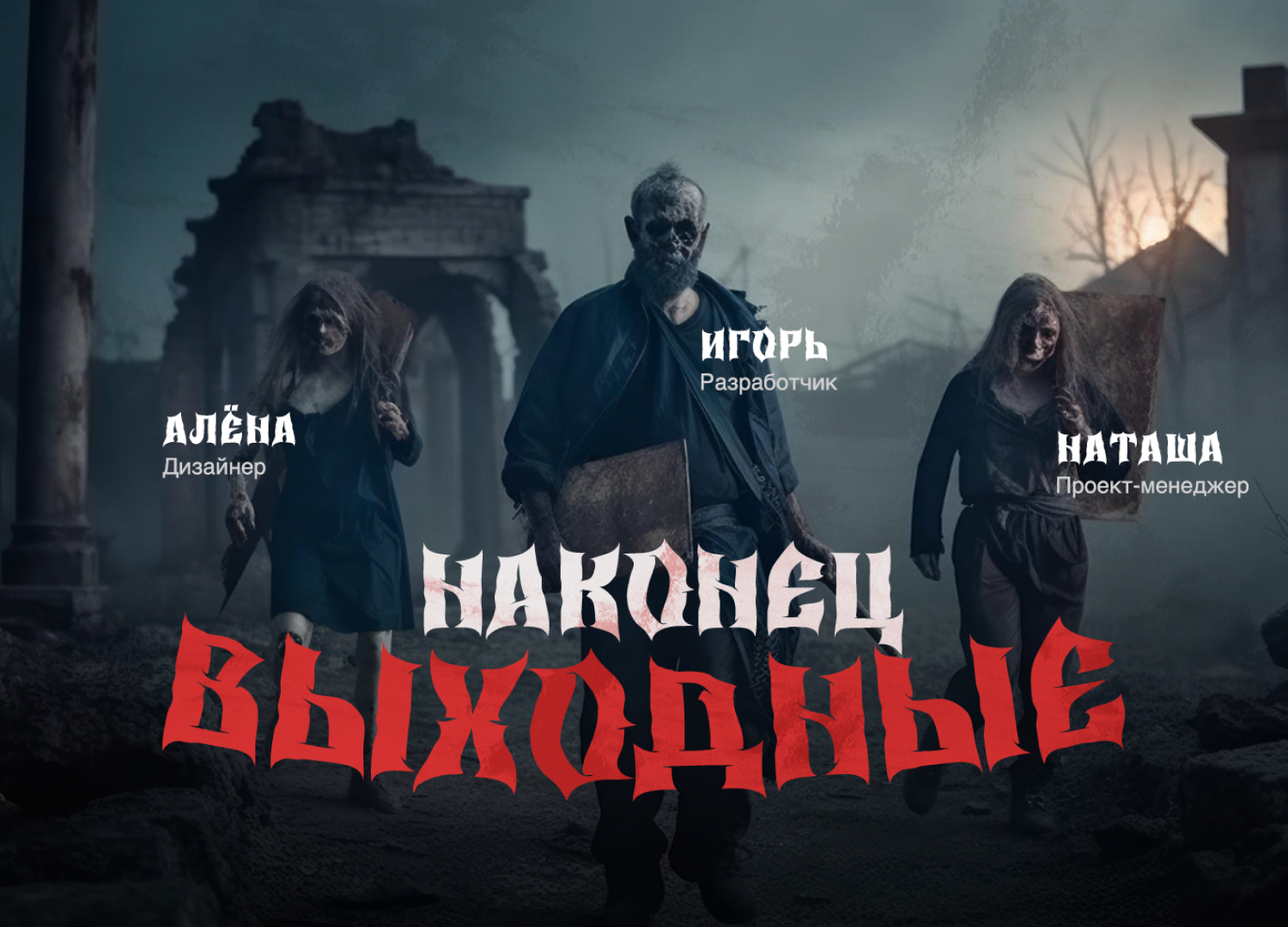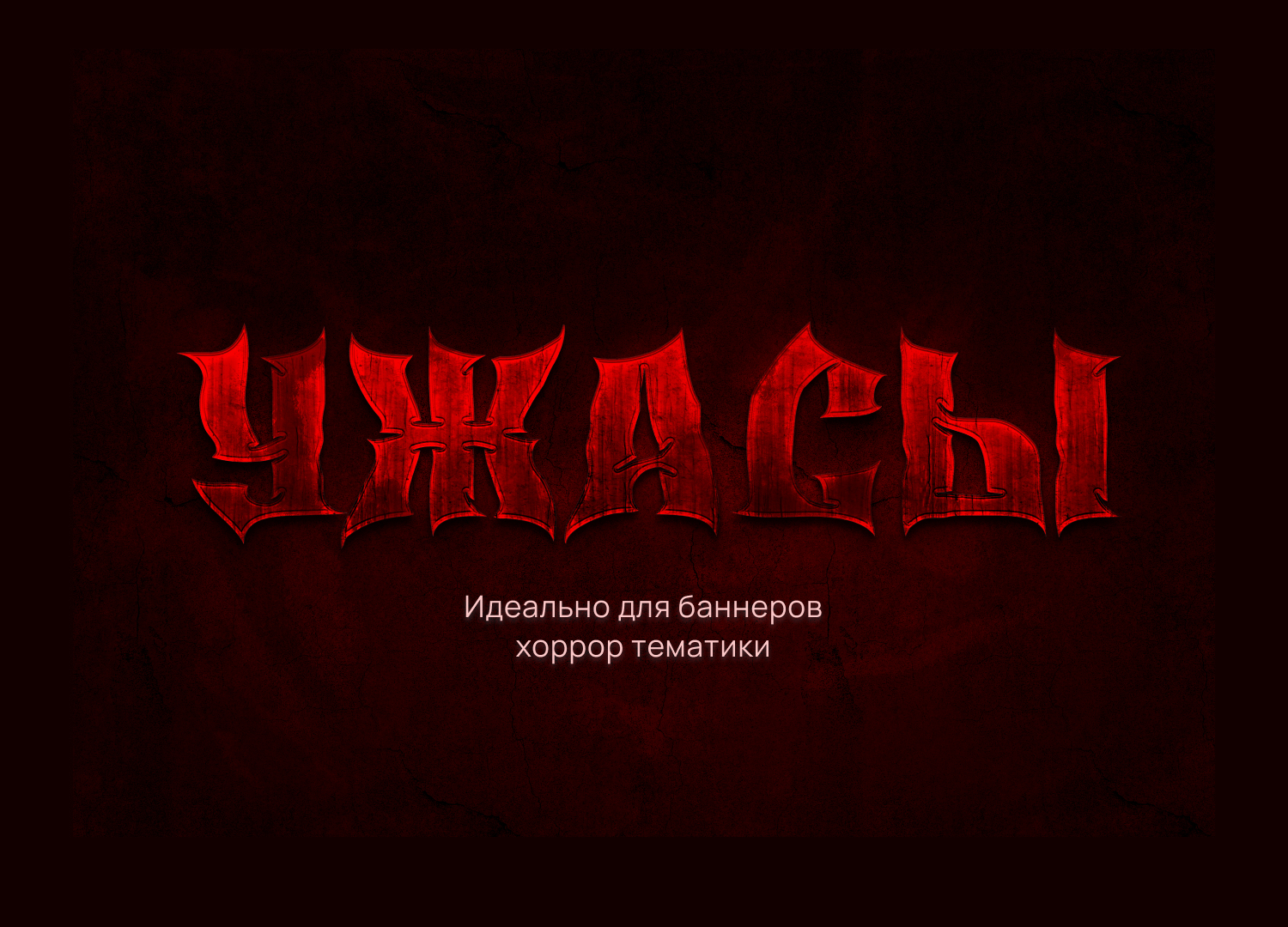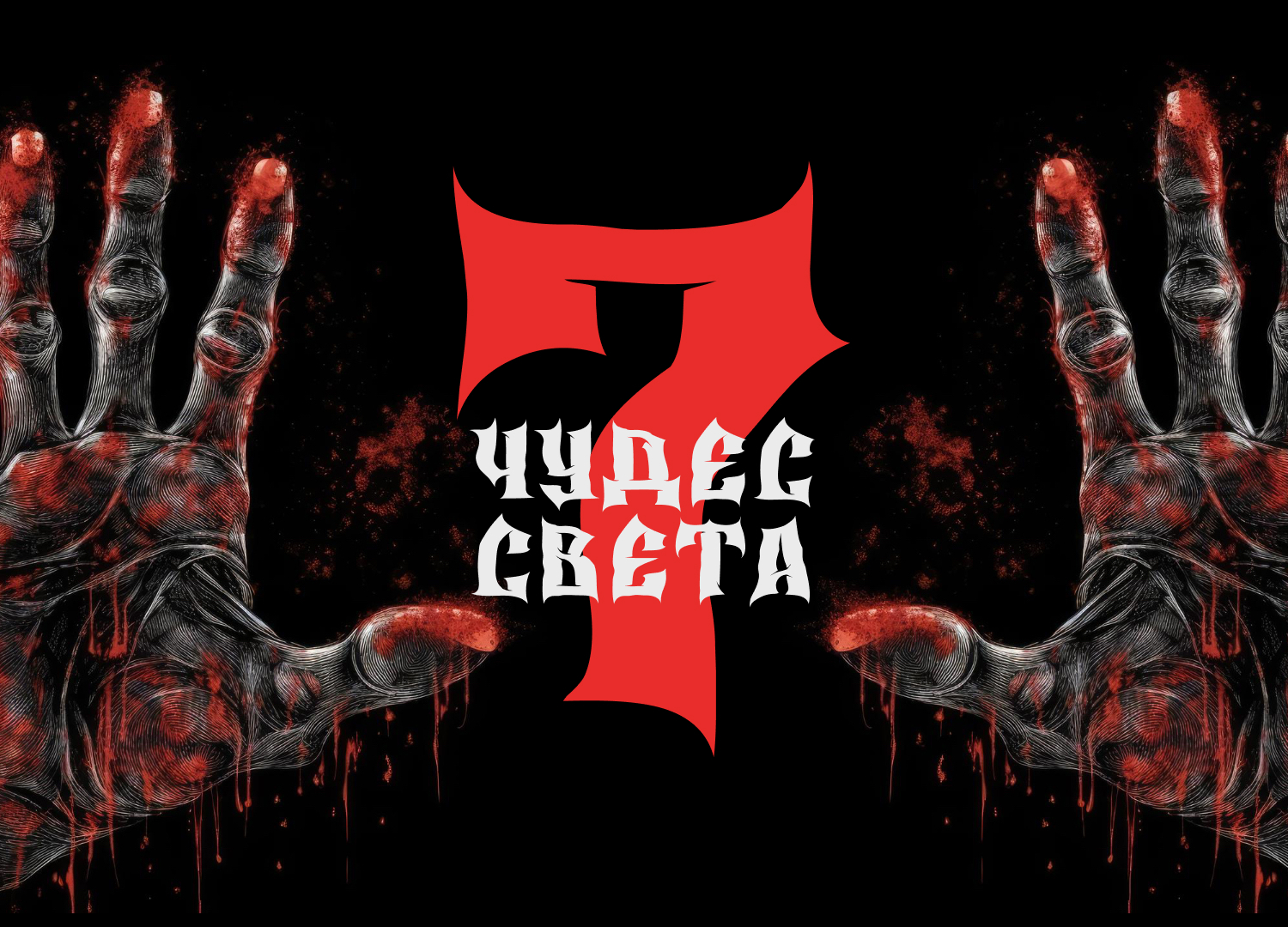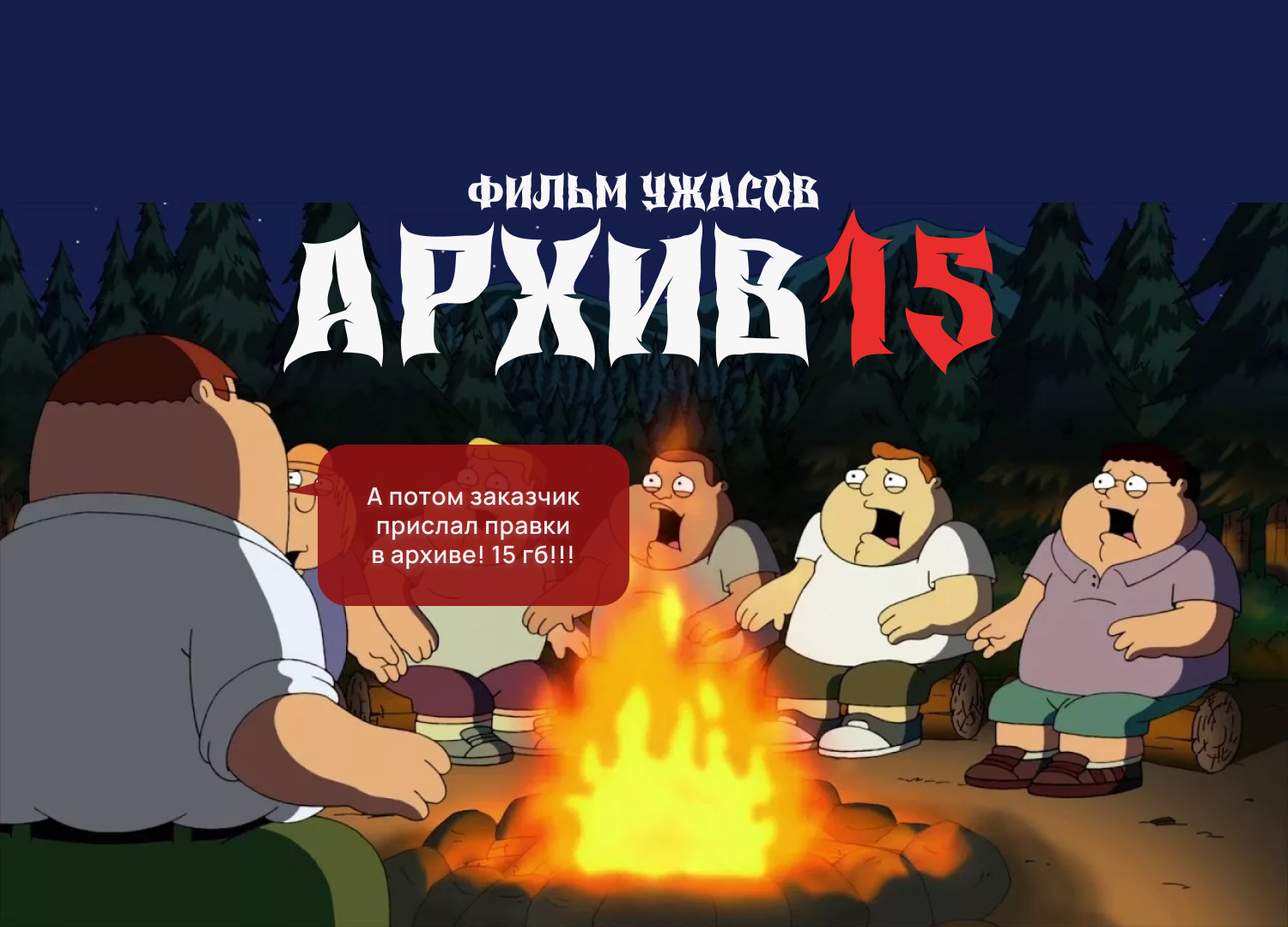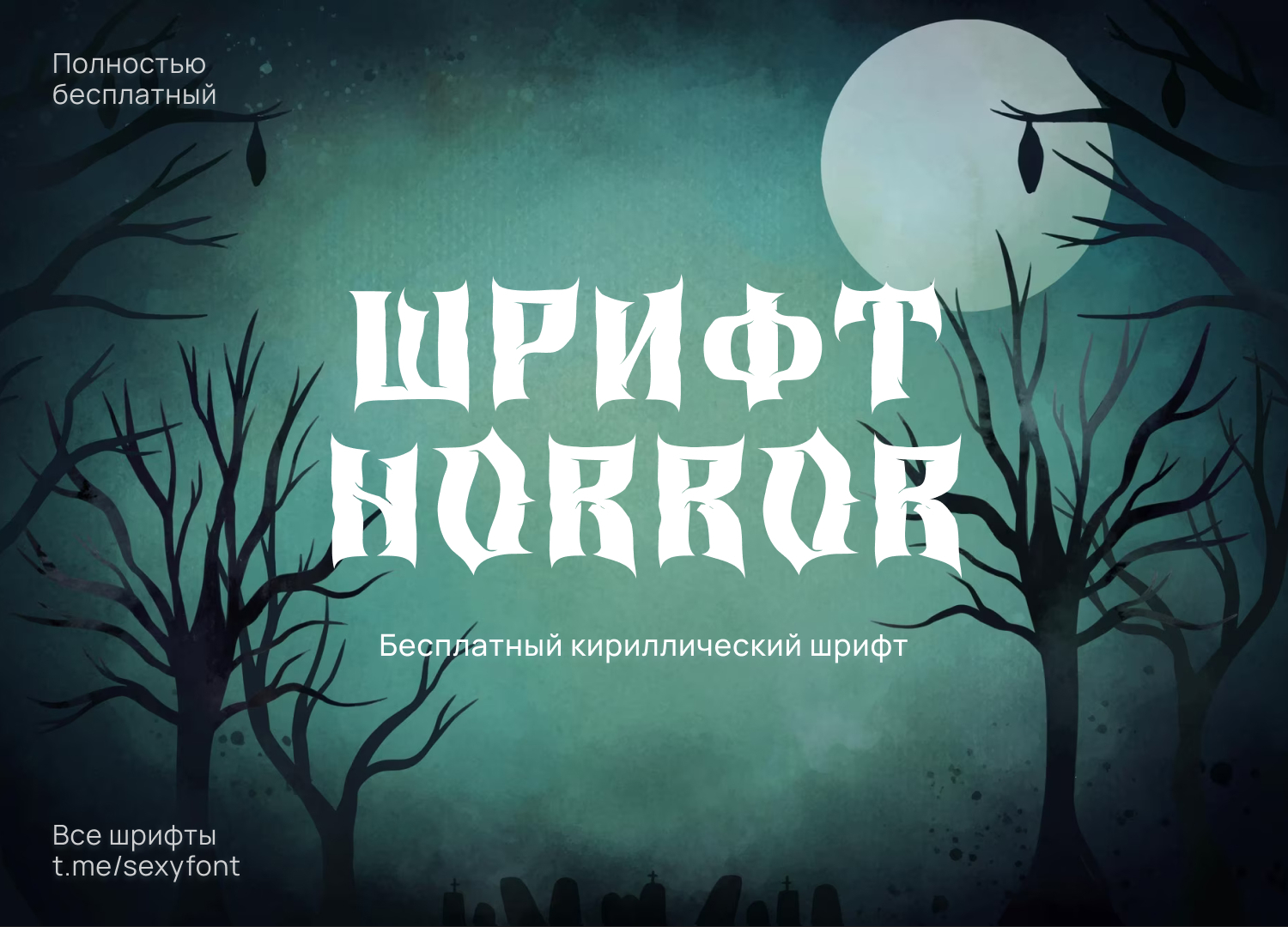
Шрифт Horror
Страшилочки подъехали! Horror. Бесплатный готический стиль с поддержкой кириллицы. Идеально для тематических баннеров. Сохрани его на всякий случай) Готика здесь не так часто. Автор: toughcrest. Бесплатно для личного и коммерции.